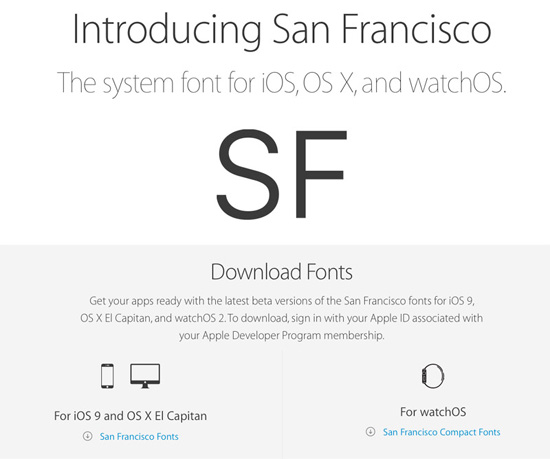
Apple выложила новый шрифт San Francisco для iOS 9, OS X El Capitan и watchOS 2
В прошлом году специально для «умных» часов Apple Watch компания Apple создала новый шрифт, при помощи которого демонстрируются уведомления на экране устройства. Позже компания решила перенести его в iOS 9 и OS X El Capitan.
Шрифт называется San Francisco и имеет девять вариантов оформления с разной насыщенностью. До этого момента он использовался только на смарт-часах и клавиатуре 12-дюймового MacBook, однако с выходом финальных версий новых программных платформ появится также на iPhone, iPad и Mac.
Ранее эксперты в области дизайна объяснили причины отказа Apple от Helvetica Neue в пользу San Francisco. По их словам, шрифт San Francisco «чёткий и хорошо различимый», он лучше читается, чем нынешний Helvetica Neue.